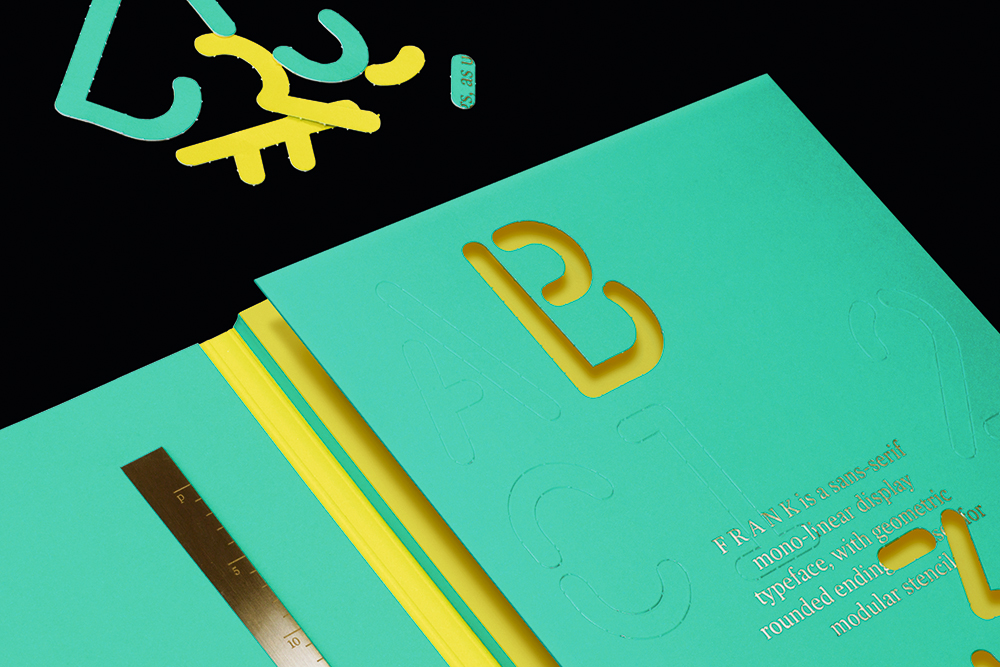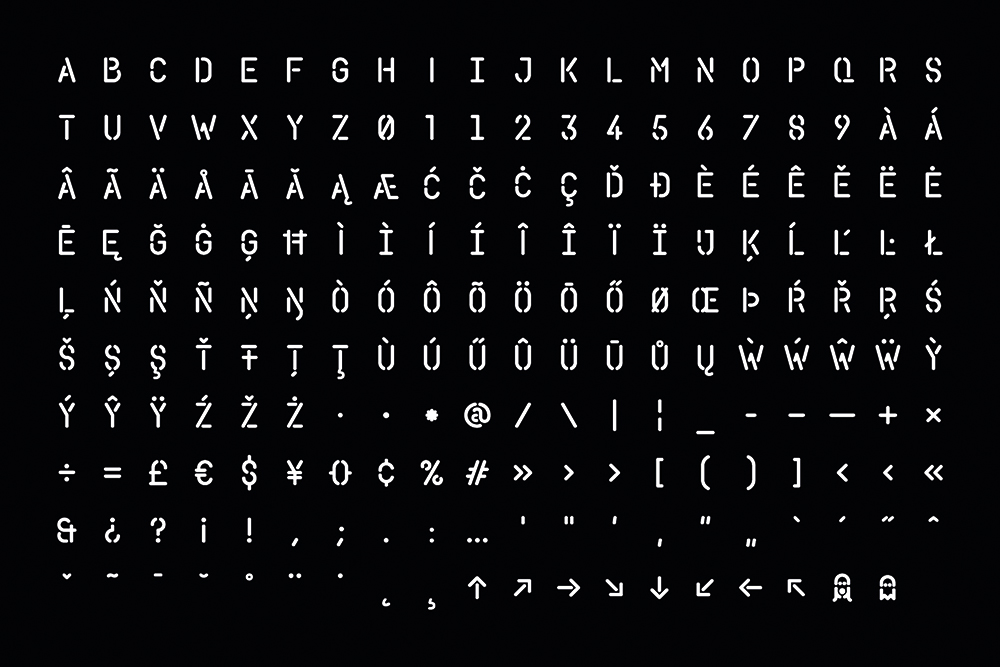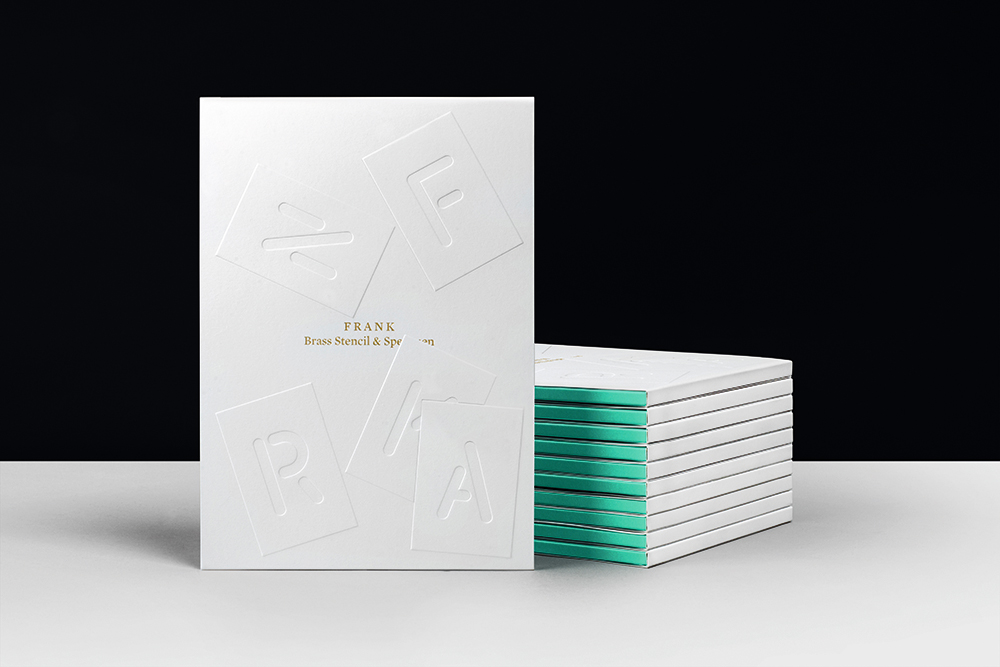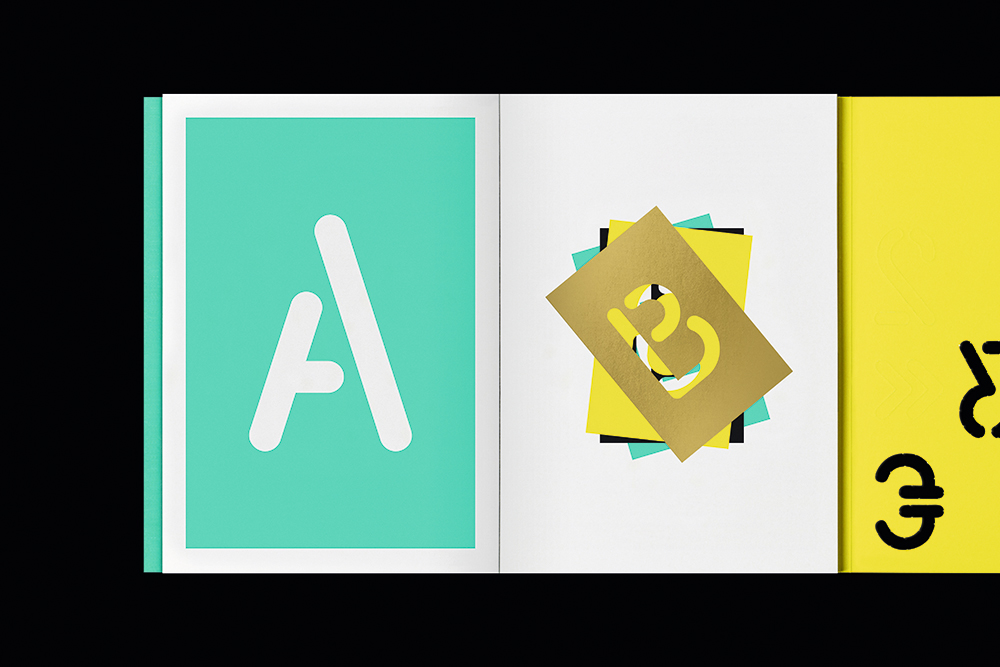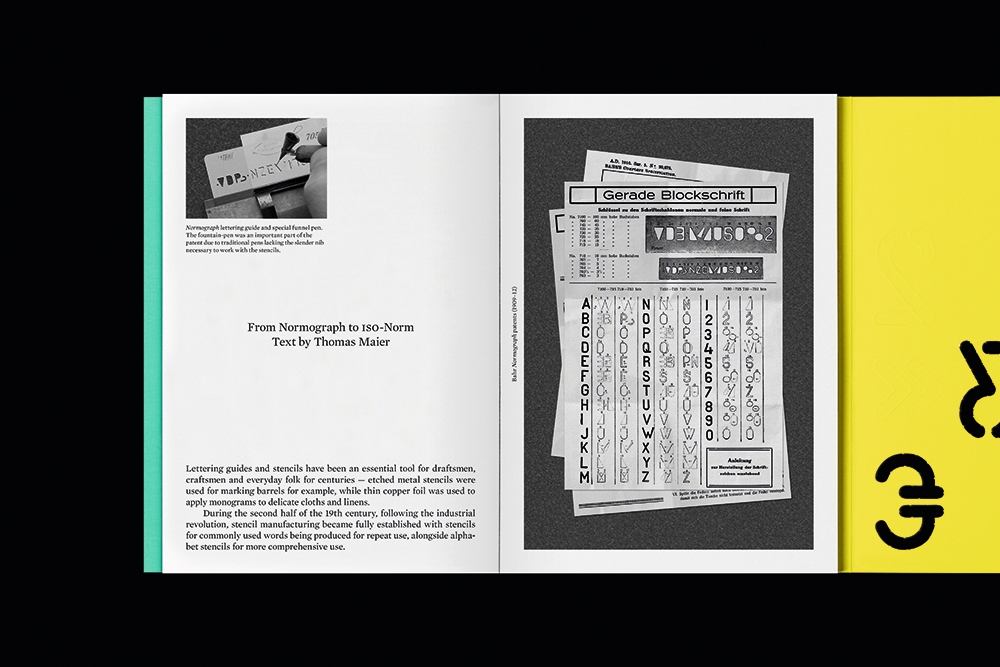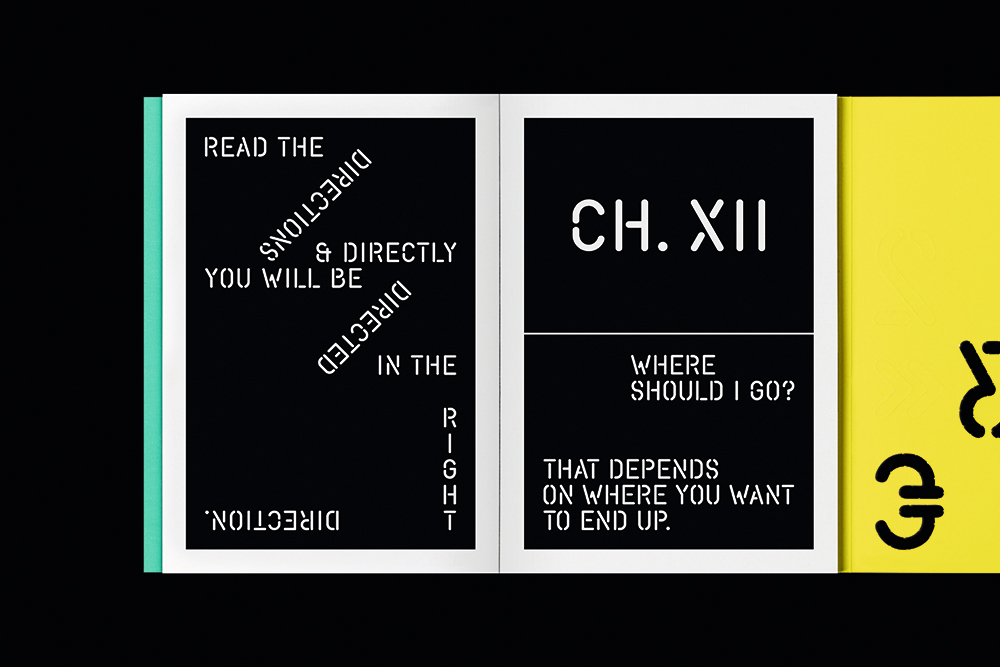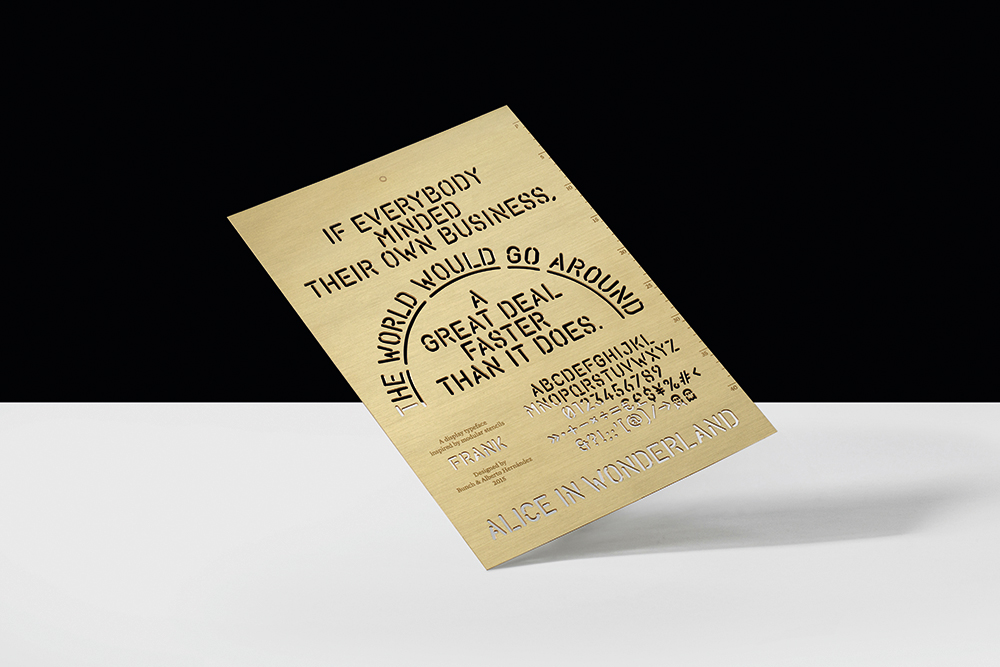
서체 ‘프랭크(FRANK)’ : 완전하게 노골적인
프랭크는 스텐실 서체로, 2013년 인쇄 프로덕션 스튜디오인 체로프스키(Cerovski) 리브랜딩을 위해 특별히 제작된 서체이다. 후에 밀리외 그로테스크가 상업적인 서체 세트로 발전시켰다.
서체 ‘프랭크(FRANK)’ : 완전하게 노골적인
이 산세리프 디스플레이 서체는 선반 밀링(lathe-milling)의 전형적인 전통을 따르고 있다. 대체 글리프 세트와 추가적인 화살표들을 포함해 207개의 글리프를 갖고 있으며, 오픈타입(포스트스크립트용)과 웹 오픈 폰트 형식도 지원한다.
레딩대학교의 부교수 에릭 킨델(Eric Kindelhe)과의 대화 이후에 팀원들은 스텐실의 세상을 보다 탐구하는 것에 대해 용기를 얻었다. 체로프스키 리브랜딩에 대한 긍정적인 반응을 토대로 하여 그들은 프랭크를 모두가 사용하고 갖고 놀아볼 수 있는 폰트로 발전시킨 것이다.